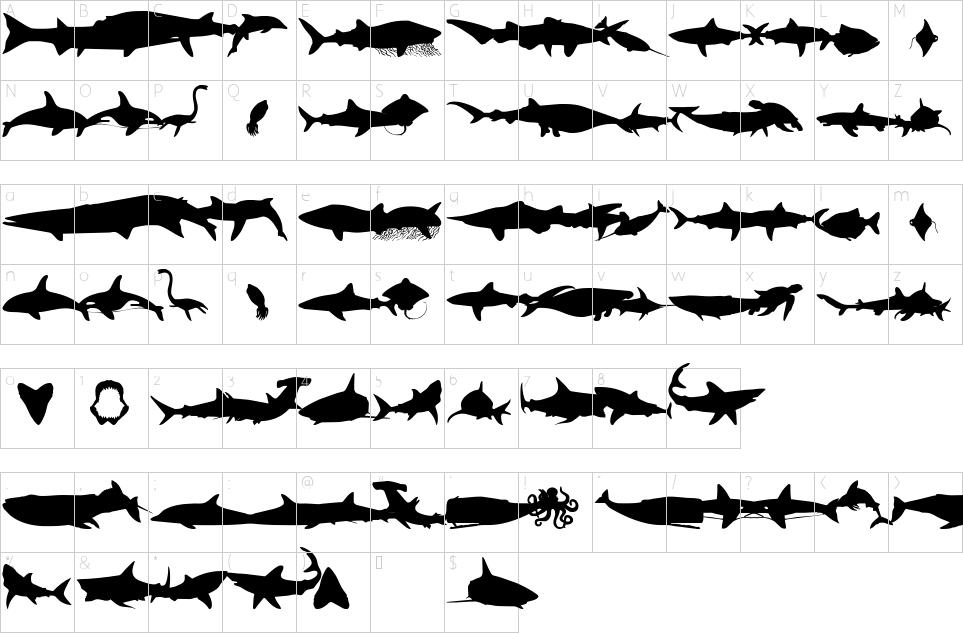
Giants Of The Sea Font – Download Grátis
Descubra a tranquilidade das águas profundas com a fonte Giants Of The Sea. Desenhada pela Iconian Fonts, esta elegante fonte se destaca no mundo dos materiais gráficos digitais. Inspirada nas vastidões marinhas, ela traz uma sensação de calma e paz para seus projetos. Com seu design simples e sofisticado, a Giants Of The Sea não apenas complementa sua criação, mas também torna-a mais atrativa e profunda. O design foi baixado 26,612 vezes, evidenciando seu valor como fonte de alta qualidade disponível para todos os dispositivos, seja em Windows ou Mac. Experimente Giants Of The Sea hoje e transforme sua maneira de gerar conteúdo digital.